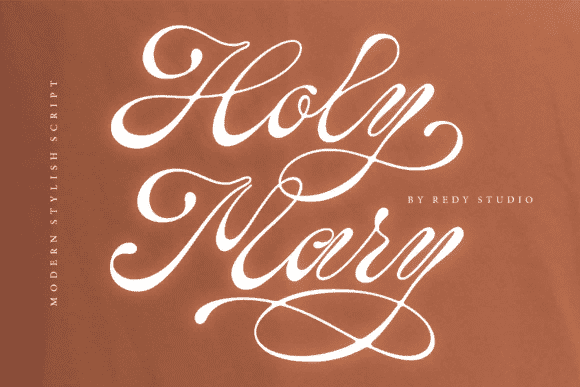
Название: Holy Mary Font (2021)
Holy Mary - это непринужденный, шикарный и причудливый шрифт.
Название: Holy Mary Font (2021)
Holy Mary - это непринужденный, шикарный и причудливый шрифт.